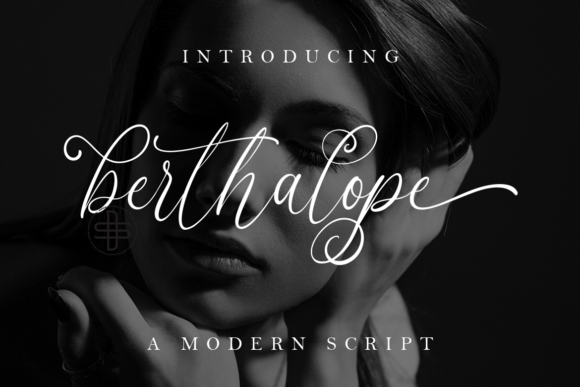
Berthalope
Si buscas recursos de alta calidad como Berthalope, este paquete premium es una opción fantástica para tus proyectos creativos.
Ya sea que estés creando productos POD (impresión bajo demanda), invitaciones de boda o gráficos para redes sociales, Berthalope es una opción ideal.